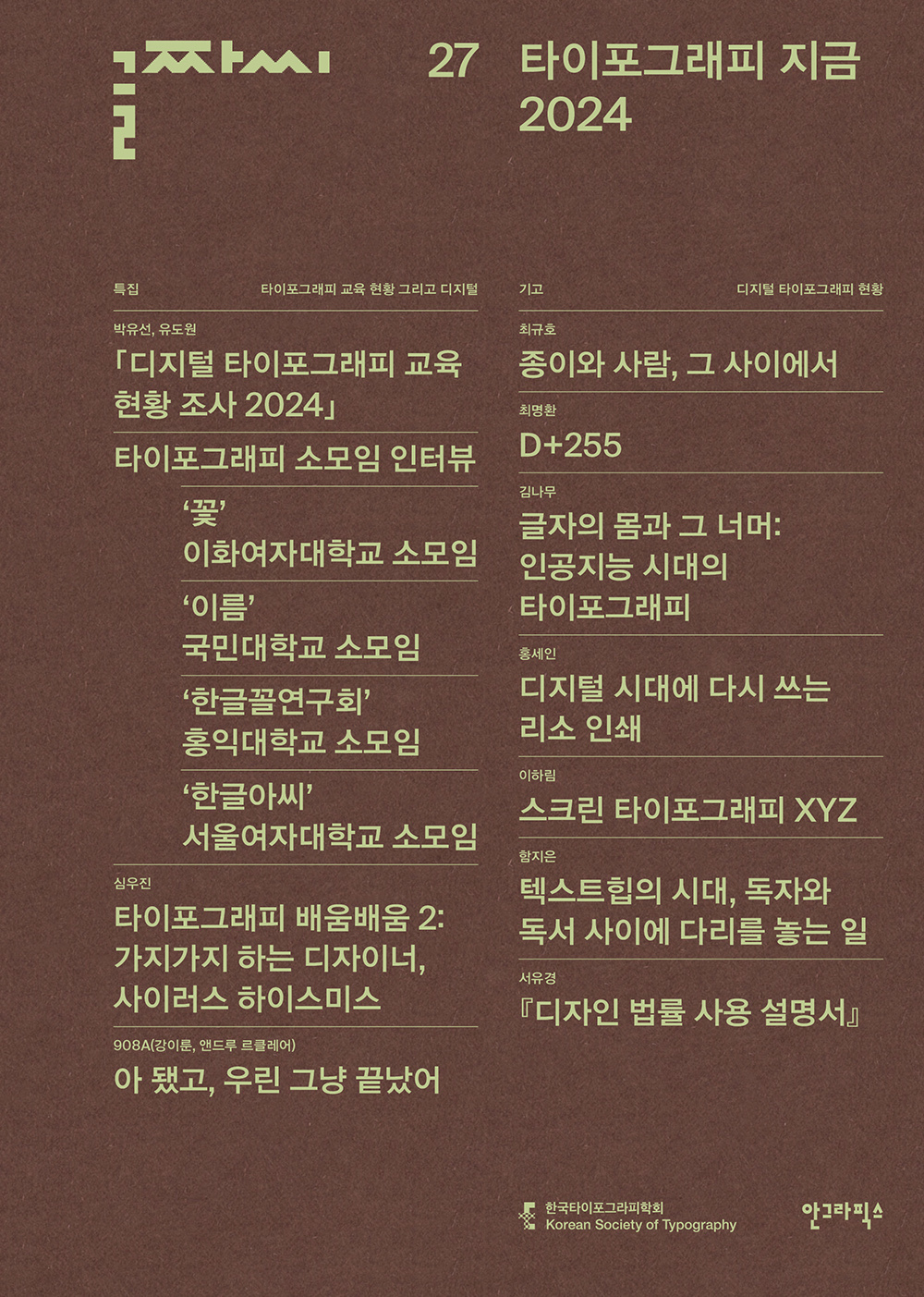
글짜씨 27: 타이포그래피 지금 2024
제8대 한국타이포그라피학회는 디지털 환경 속에서 타이포그래피의 현상과 실천을 탐구하며 동시대 타이포그래피의 정체성을 모색하고 있다. 『글짜씨 26』이 ‘지금까지의 타이포그래피‘를 다룬 데 이어, 『글짜씨 27』은 ‘지금의 타이포그래피’를 주제로 2024년 현재의 변화와 흐름을 기록한다. 올해 디지털 협업의 시대를 상징하는 노션 사용자가 1억 명을 돌파했고, 월간 『디자인』이 20년 만에 판형을 바꾸며 종이 매체를 넘어 디지털 플랫폼으로 확장했다. 또한 기업 글자체, 커스터마이징 글자체는 10년, 20년의 역사를 넘어 서사를 담아내며 한국 현대 시각 문화에서 큰 비중을 차지한다. 이번 호에서는 디지털 환경과 타이포그래피 교육, 기업과 정부 프로젝트, 독립 디자이너의 작업 및 주요 이벤트를 통해 타이포그래피의 현재를 다각도로 탐구한다.
『글짜씨』는 2009년에 창간해 지난 15년간 학회 구성원과 국내외 타이포그래피 연구자, 디자이너의 연구 성과를 기록한 학회 학술지입니다.